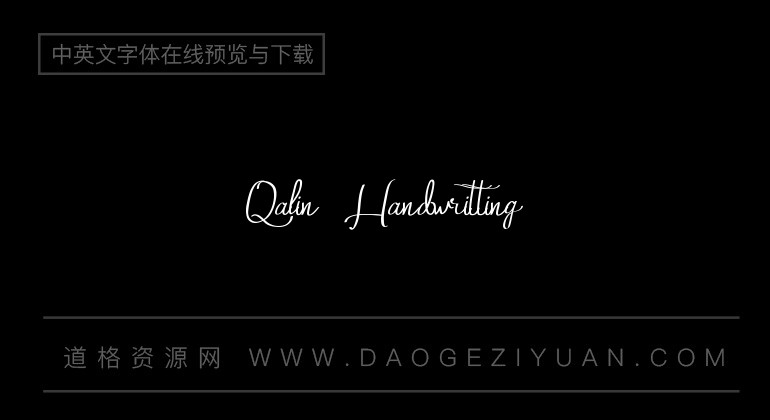
Qalin Handwriting是一种优美的手写字体,其特点是自然流畅、轻盈柔美。这种字体的笔画线条优雅,具有一定的艺术性,非常适合用于各种创意设计和文学创作中。 Qalin Handwriting字体的外形美观,具有良好的可读性和印刷效果,适用于各种印刷品的设计。此外,这种字体还支持多种语言和字符,比如中文、英文、日文等,可供全球各地的设计师和创作者使用。 总之,Qalin Handwriting是一种非常优美、自然流畅、具有艺术性的手写字体,适用于各种设计和文学创作场景。内容介绍
Qalin Handwritting是一款非常不错的手写艺术字体,具有很好的视觉感,适合于文化类的宣传设计、商业类品牌的广告和产品包装设计以及个性化文字排版等较多场景。